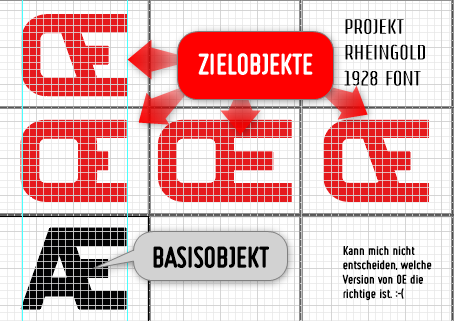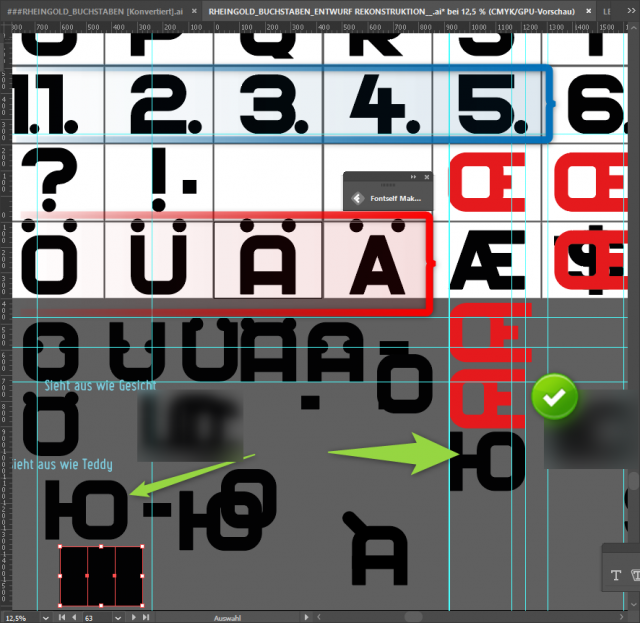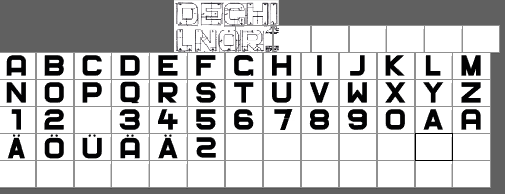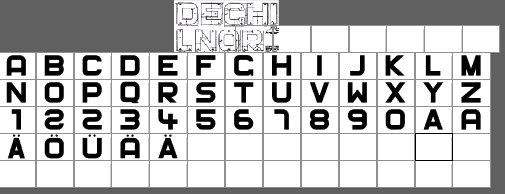
Rheingold Schrift
Hallo, ich bin mir nicht sicher ob es hier in der Rubrik rein passt.
Ich hab mir mal den Spass gemacht die Rheingoldschrift nachzubauen. In einem Buch hatte ich dazu eine Zeichnung gefunden. Auch in Wikipedia konnte ich für den Buchstaben "R" auch Maße erkennen.
Jetzt stehe ich vor dem Problem welche Zahlen hier besser passen würden.
Besonders die 2 , 3 6 und 9 bereiten mir etwas Kopfschmerzen. Sollte man besser bei 6 und 9 den Strich oben/unten durchziehen oder eher so lassen? Ein wenig wirken sie jetzt schon zu modern. bei der 2 und 3 könnte man sich auch einen "Auf- und Abstrich" vorstellen, wie man es bei C oder G sieht.
Dann noch die Frage ob es Sinn macht hier auch cyrilische Buchstaben dafür zu bauen?
Hallo Dean,
Hier mal ganz schnell, wie ich wohl die Ziffern gelöst hätte:
Originellerweise hatte ich grad auch eine Schrift mit recht ähnlicher Formensprache am Wickel. Da hatten wir letztens jemand, der ältere Trikot-Ziffern suchte.
Hier war dann eine Darstellung der Ziffern mit und ohne Markenlogo.
Ich dachte mir, mach dir doch auch den Spass, und bau aus nur den Ziffern eine komplette Schriftart, als durchgängige Triline-Schrift. Komplett mit Akzenten, rundem s und Ligaturen, wahlweise doppelstock a und Brillen g per SS01 in einstöckiges a und dazu passendem g, natürlich ẞ - und dann auch Kyrillisch, mit OT-Unterstützung der anderen Kleinbuchstaben für Serbisch und Bulgarisch.
hey klasse Peter die gefallen mir auch besser die Zahlen. Wenn man sich nicht entscheiden kann, hat man ja immernoch die  alternativen Varianten. wie z.B das "A"
Und das letzte Zeichen geht für mich glatt als kyrillisches G durch, verwendet man, was zu der Schrift sicher gut passt, die alternativen Formen aus der Schreibschrift, wie ich es hier gemacht habe: Inkopins clusters
Auch wenn es hier natürlich eine durchgehende Minuskelschrift ist, aber ich habe diese Formen auch schon als Großbuchstaben gesehen.
ja irgend wie erinnert die wirklich an fussball
jetzt bin ich auf dem Weg zum cyrillischen doch auf ein problem gestoßen. einige buchstaben sind ja in der horizontale so ausladend dass man sie nicht wirklich verwenden kann.
Wenn man sich jetzt die vorgabe als regel setzt, ist jedes zeichen 215mm breit 230mm hoch die große rundung hat 70mm und die kleine 18mm. die strichstärke ist 52mm wenn man da ein "JU" oder ähnliche buchstaben bauen muss wird es verdammt eng.
wie würdest du das lösen Peter?
@catfonts Hallo Peter,
kann mich nicht entscheiden, welche Version die optisch richtige Version von OE ist.
Ganzrechts oder ganz unten sind identisch nur wirkt die schräge zu modern für RHEINGOLD 1928, die andere version ist zu breit und wiederum die andere wirkt optisch so, als wäre der mittelbalken für das E zu kurz.
Welche Version würdest du nehmen. vermutlich keine ;-) also als basis habe ich O*E genommen und sie so gestutzt das  es passt. vermutlich sollte ich nicht AE als basis nemen sondern etwas anderes. Hm, weiss gerade nicht weiter.
auf dieser Baustelle (LEILA LENSFONT), wäre die Wahl etwas einfacher.
Sieht etwas wüst aus ich weiss, aber Baustellen sind nicht alle so sortiert ;-)
Ich würde mich jetzt für die Variante links in der mittleren Reihe entscheiden. Die Schräge kommt ja vom A, gehört hier also nicht rein. Eventuell den gemeinsamen O-E-Strich um etwa 1-2 Kästchen nach Links verschieben, sodass der O- und der E-Anteil etwa gleich breit sind und der mittlere E-Balken etwas länger wird
aber auf das "a" wie hier wäre ich wahrscheinlich nie gekommen. Das würde ich ja eher als 1  1/2-stöckiges-a betrachten :-D
Wie bei Flugzeugen, ein Doppeldecker nicht sofort ein Doppeldecker wenn er zwei Tragflächen übereinander hat, denn echte Doppeldecker, haben gleichlange Tragflächen ;-)  Ich danke dir schon mal für die nette sympatische "Aufklärung"  dieses Futura-a sieht vermutlich in fremden Augen auch aus wie eine Ligatur von o+i ohne Punkt aus und das a-hier im Text wie ein o mit gespiegelten Minuskel-s leicht gekippt.